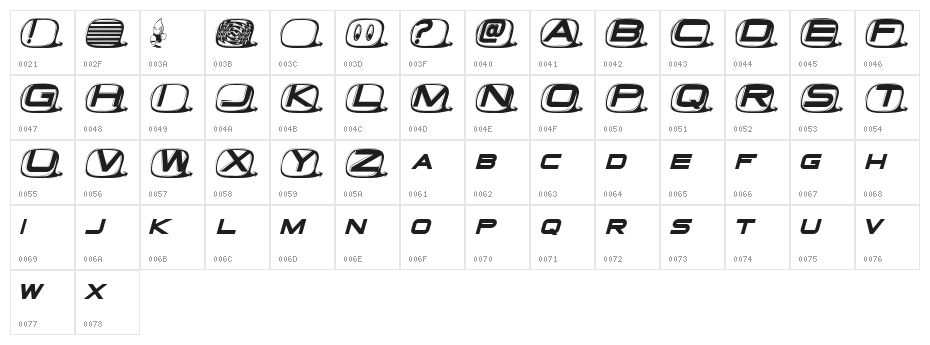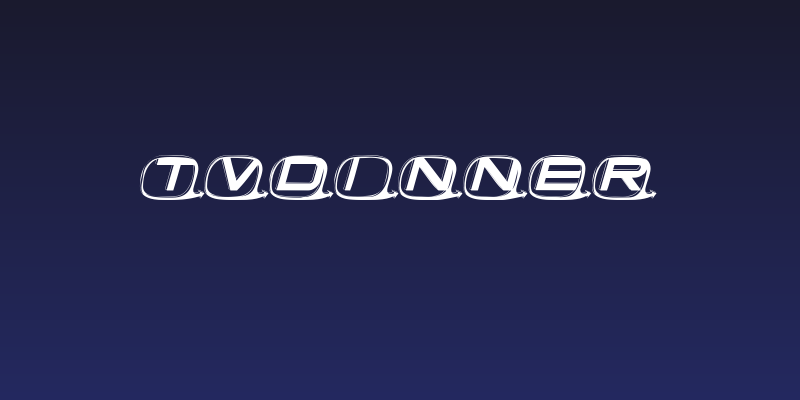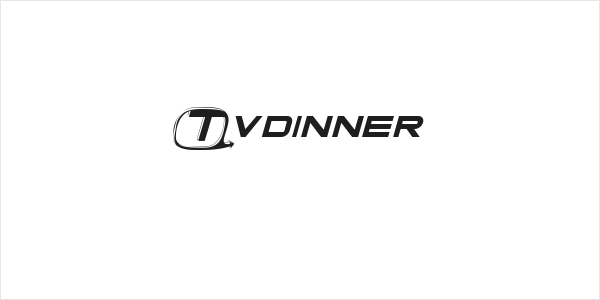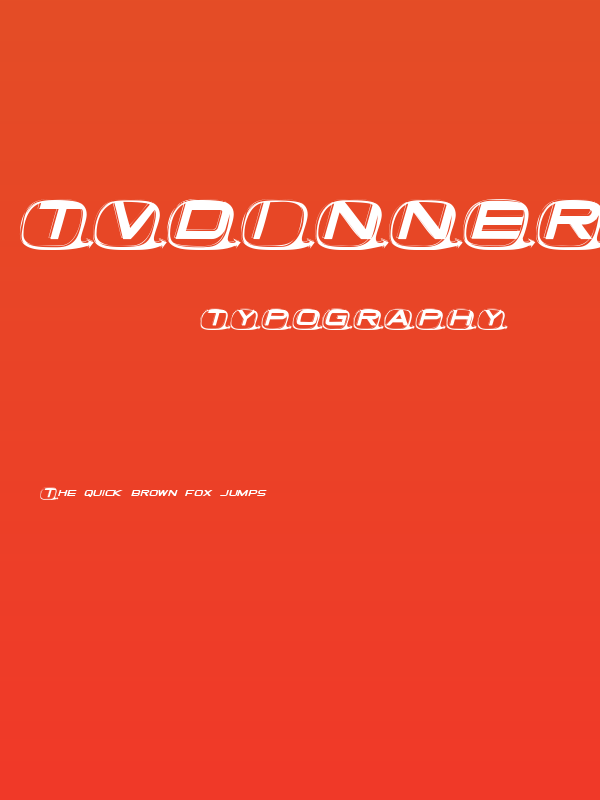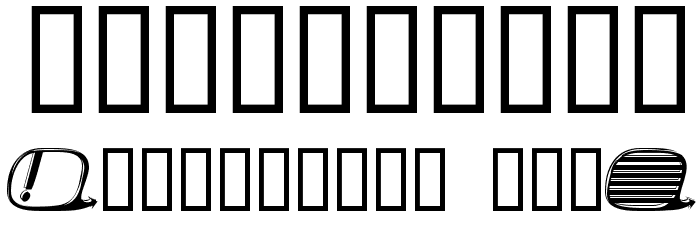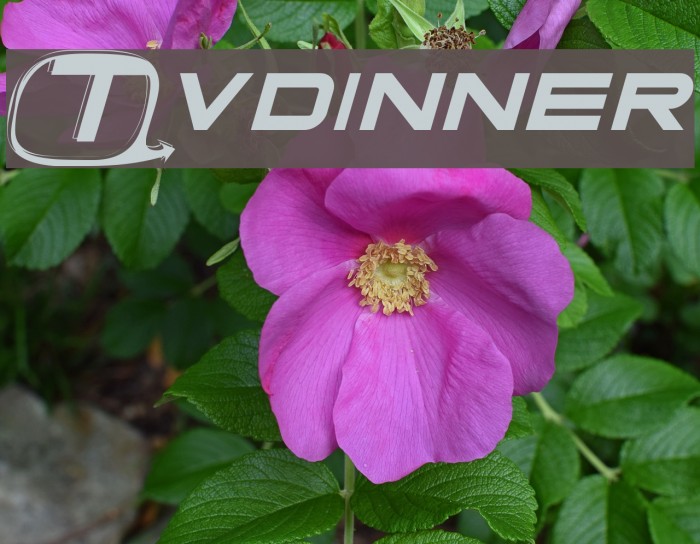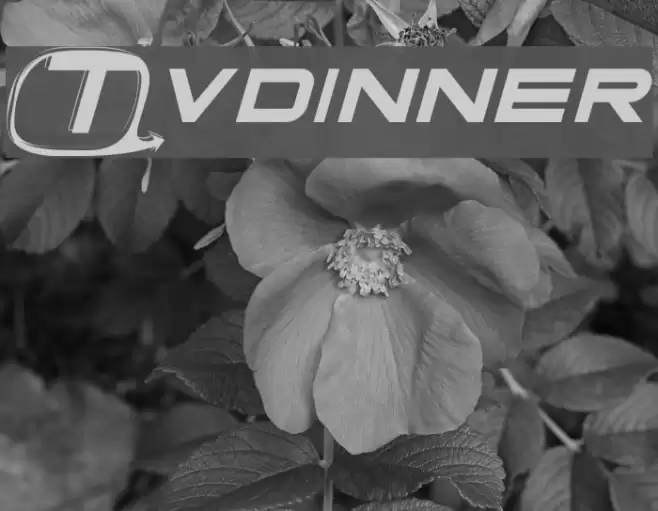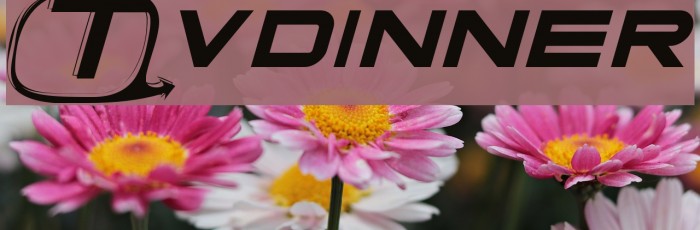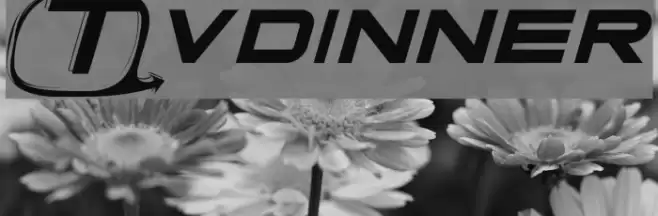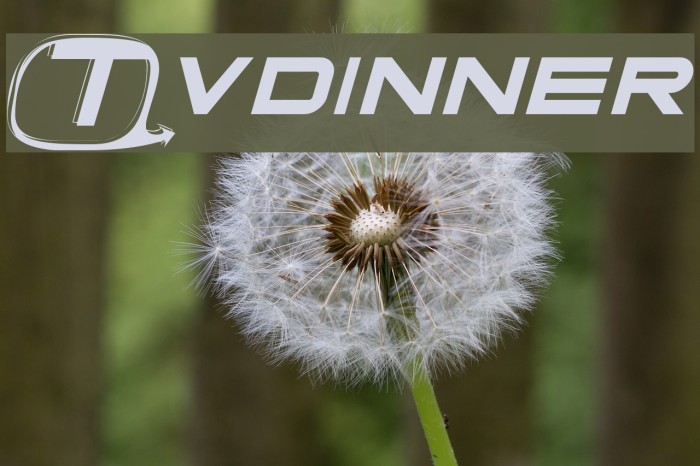
Tvdinner Font
| Рекомендуемые проекты | Ideal for projects that require a modern and energetic look, such as sports branding, tech company logos, or futuristic-themed posters. |